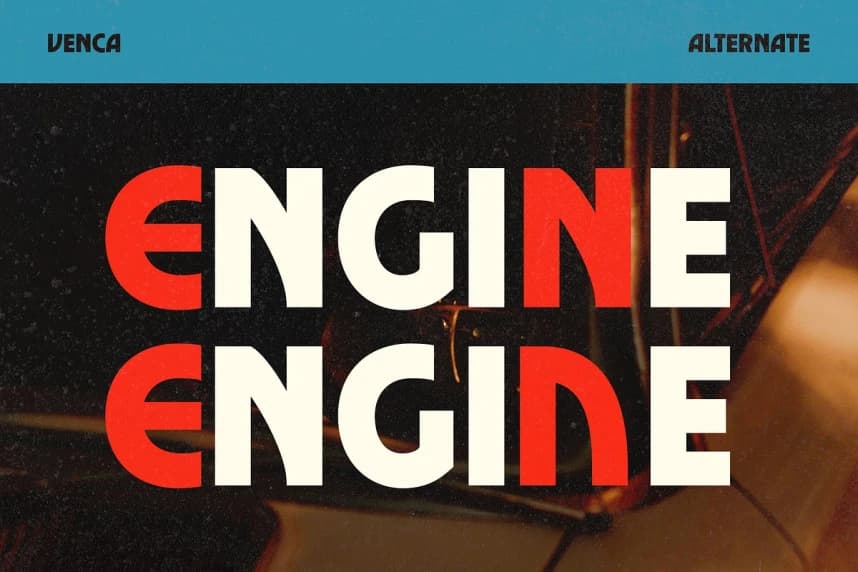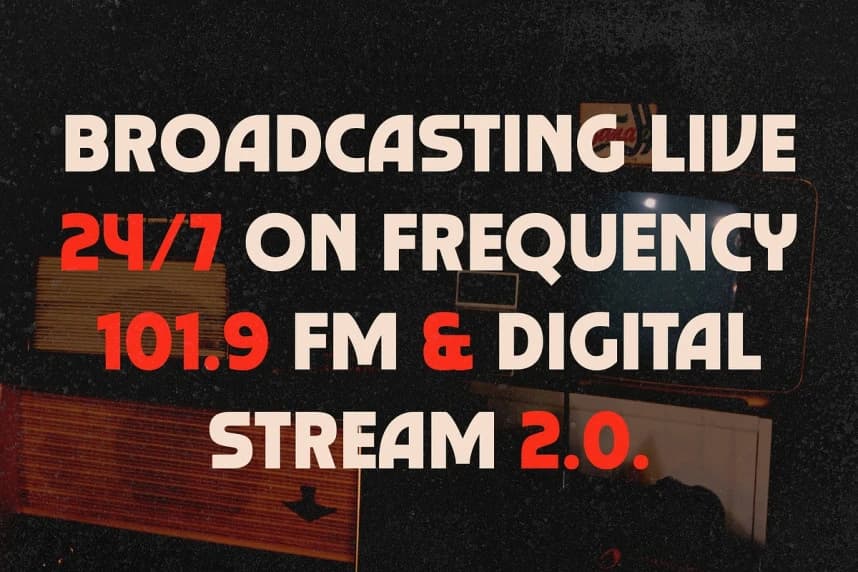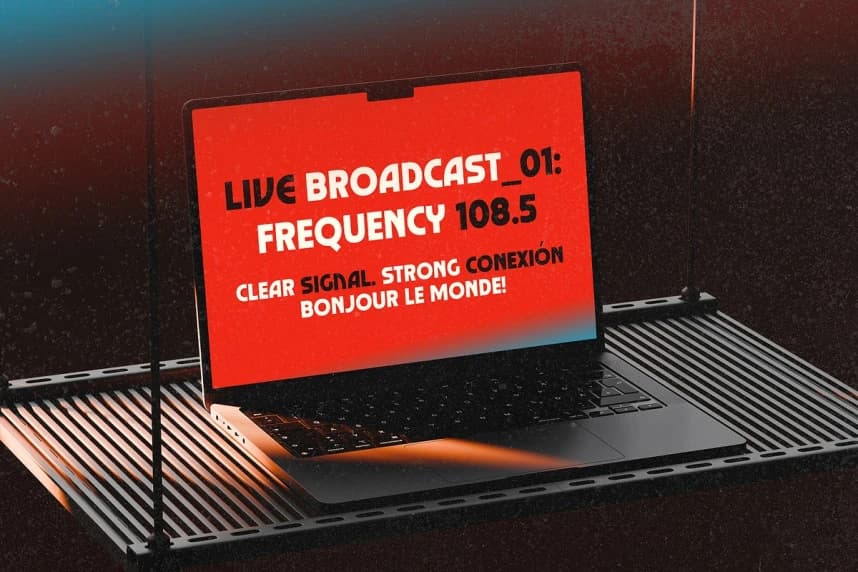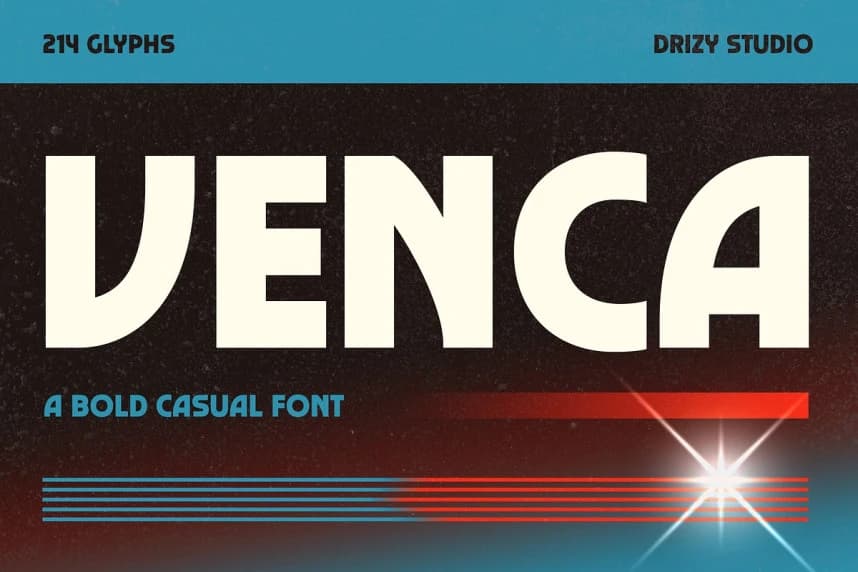
Venca Bold Font, projelerinize cesur ve arkadaş canlısı bir kişilik kazandırmak için tasarlanmış eğlenceli ve ifadeli bir sade yazı tipidir. Kalın hatları ve rahat harf biçimleriyle, oyuncu çekiciliği ile güçlü görsel etki arasında mükemmel bir denge sağlar.
Venca Bold Font, projelerinize cesur ve arkadaşça bir kişilik kazandırmak için tasarlanmış eğlenceli ve ifade dolu bir fonttur. Kalın çizgileri ve rahat hatlı harf yapılarıyla, oyuncu çekicilik ile güçlü görsel etki arasında mükemmel bir denge sağlar.